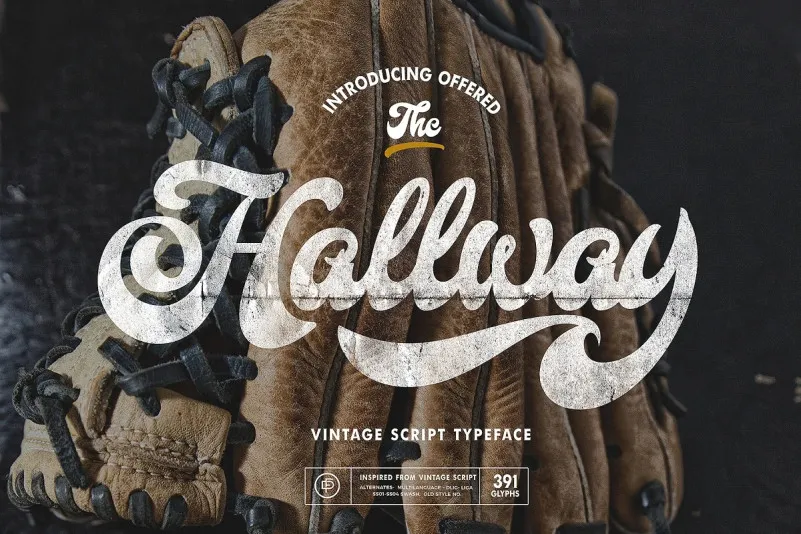
Esta é uma fonte script com traços firmes que transmite um ar vintage, projetada pela Fortunes Co., disponível no designer 99designs. Perfeita para elementos que exibam um sentido de aventura ou sofisticação clássica, como pinturas de sinais e rótulos. Se adequada a logotipos, nomenclaturas de produtos em pacotes, etiquetas e tudo o que reflete características de épocas passadas. É perfeitamente compatível com estilos vintage, especialmente para marcas de café antigas ou bares, criando um ambiente acolhedor e memorável. Se você está buscando uma fonte script robusta com toque vintage para suas próximas criações gráficas, essa é a escolha perfeita.